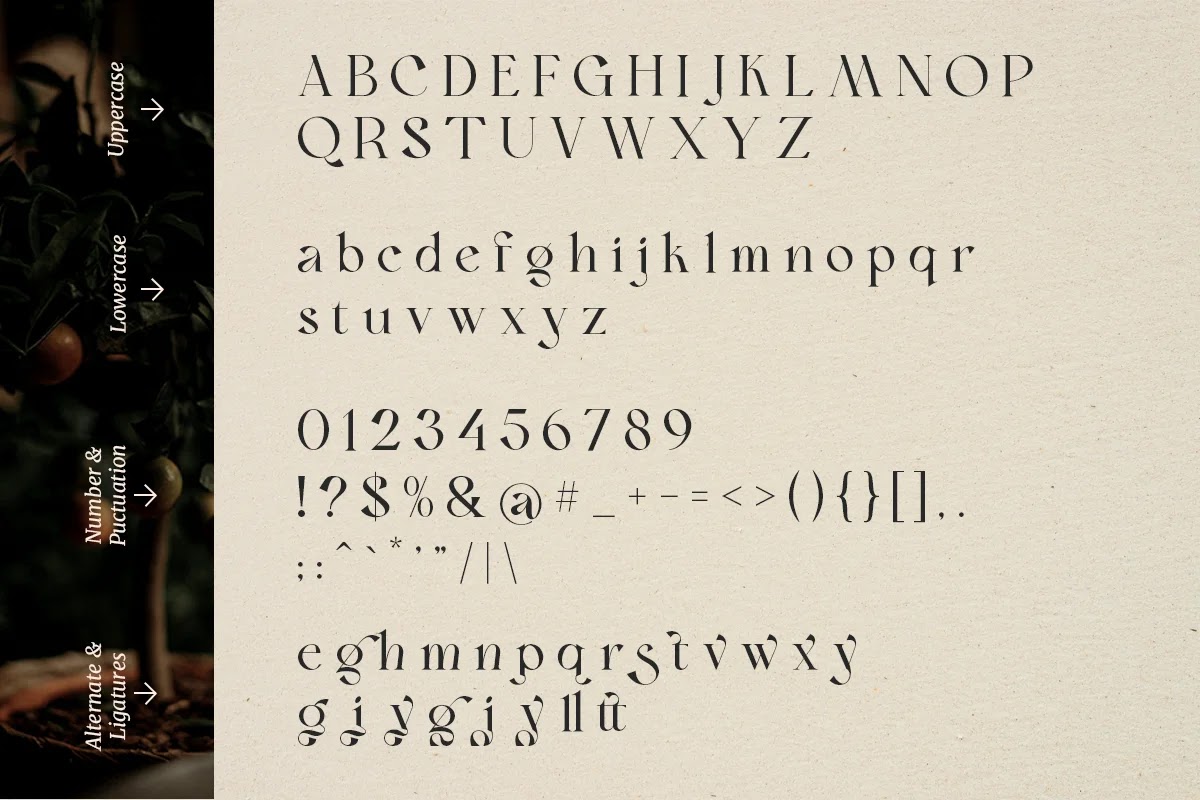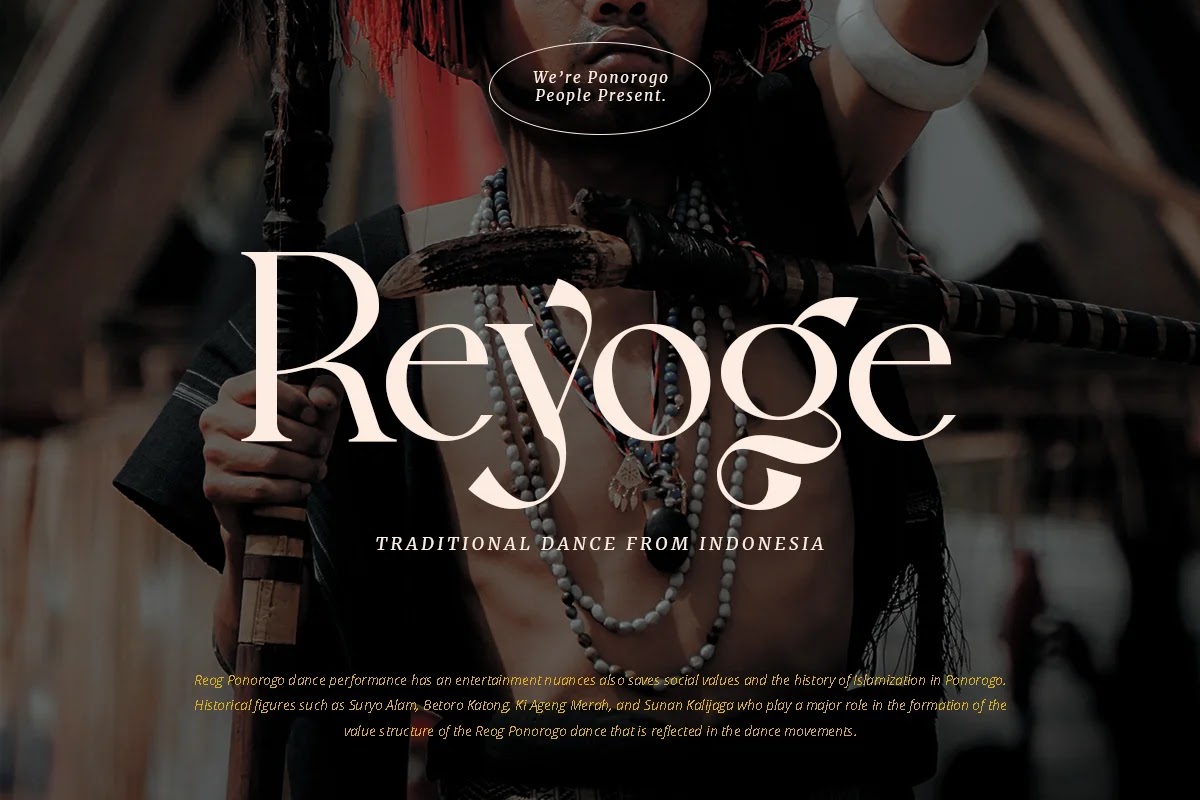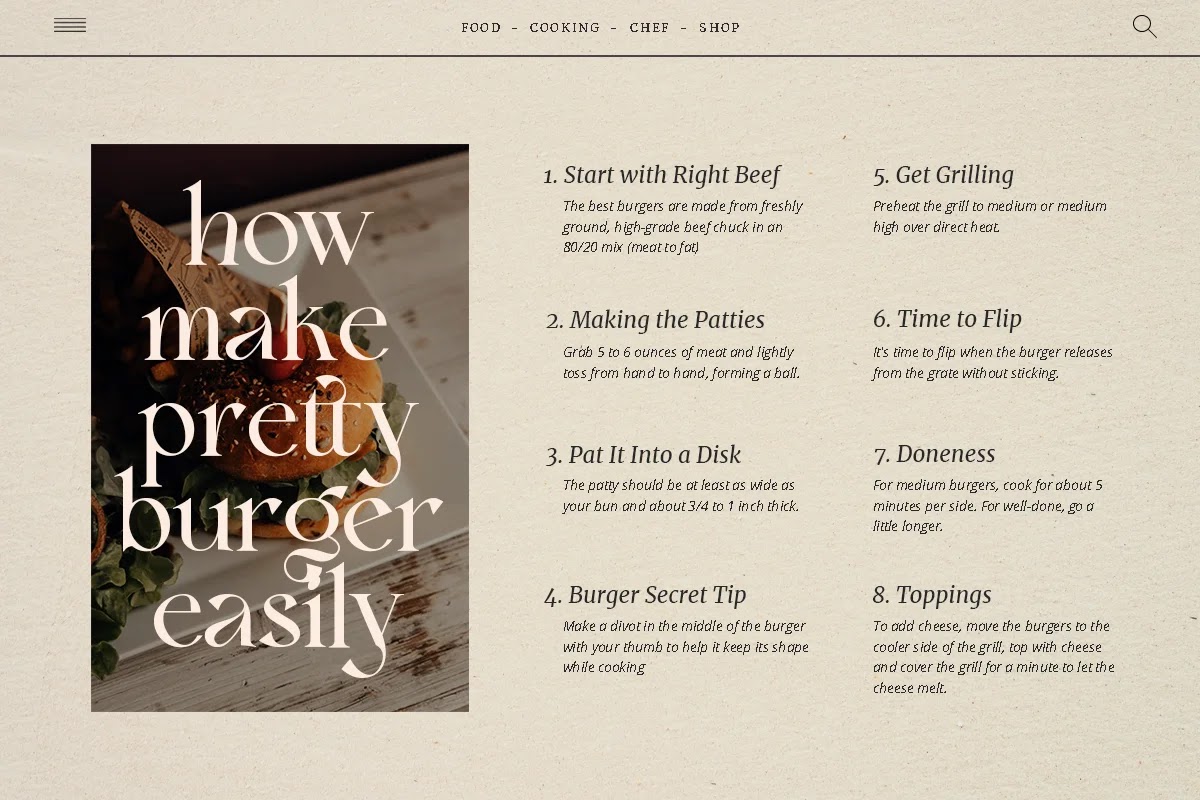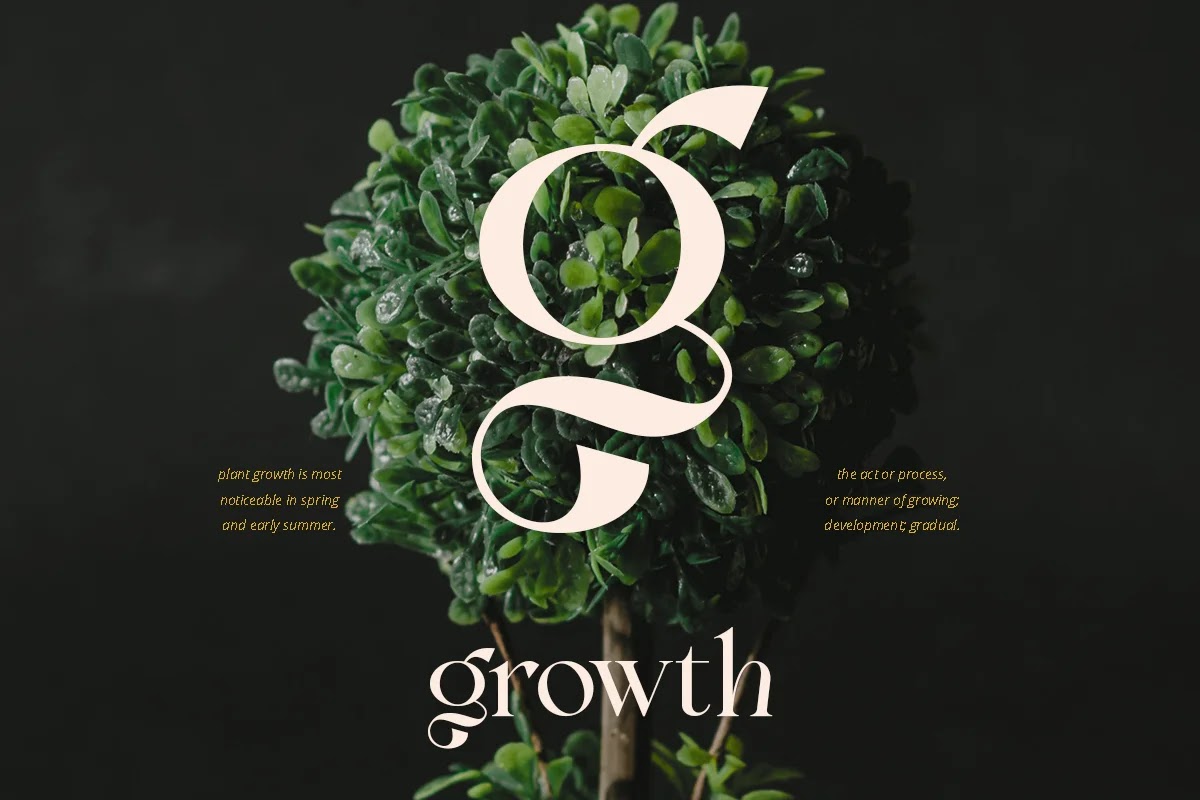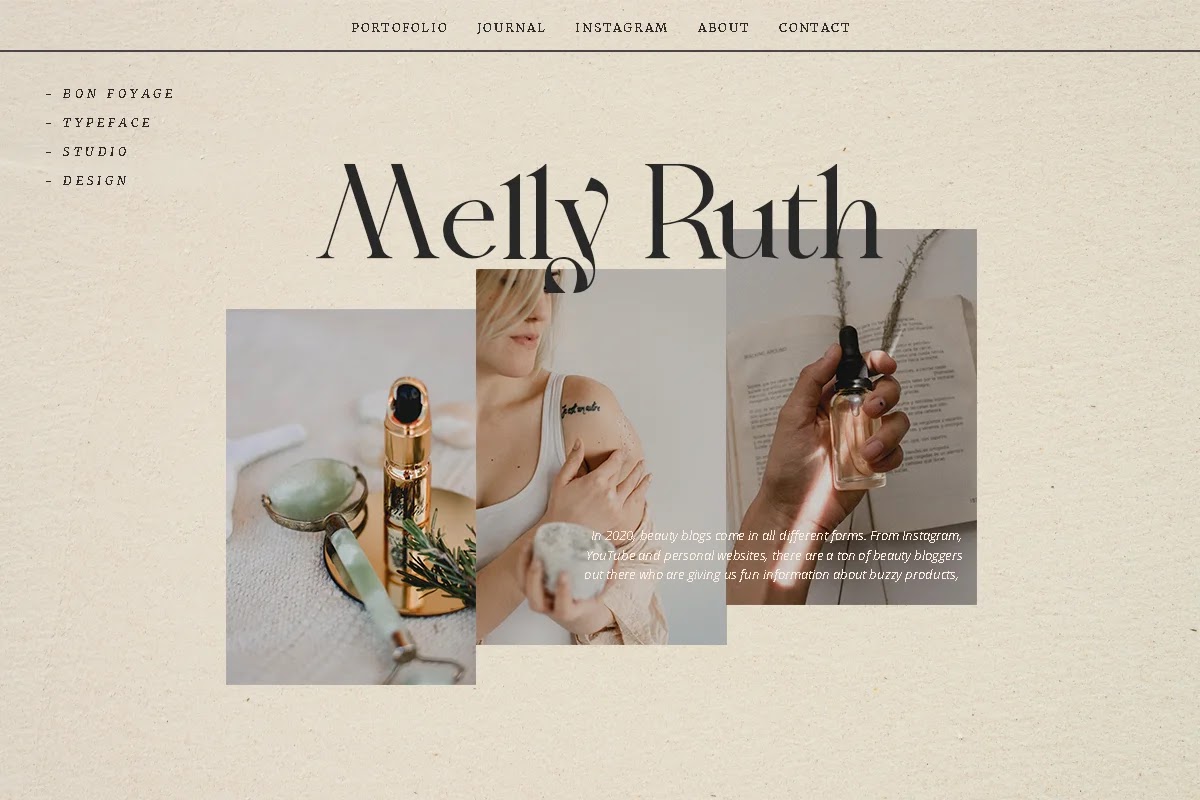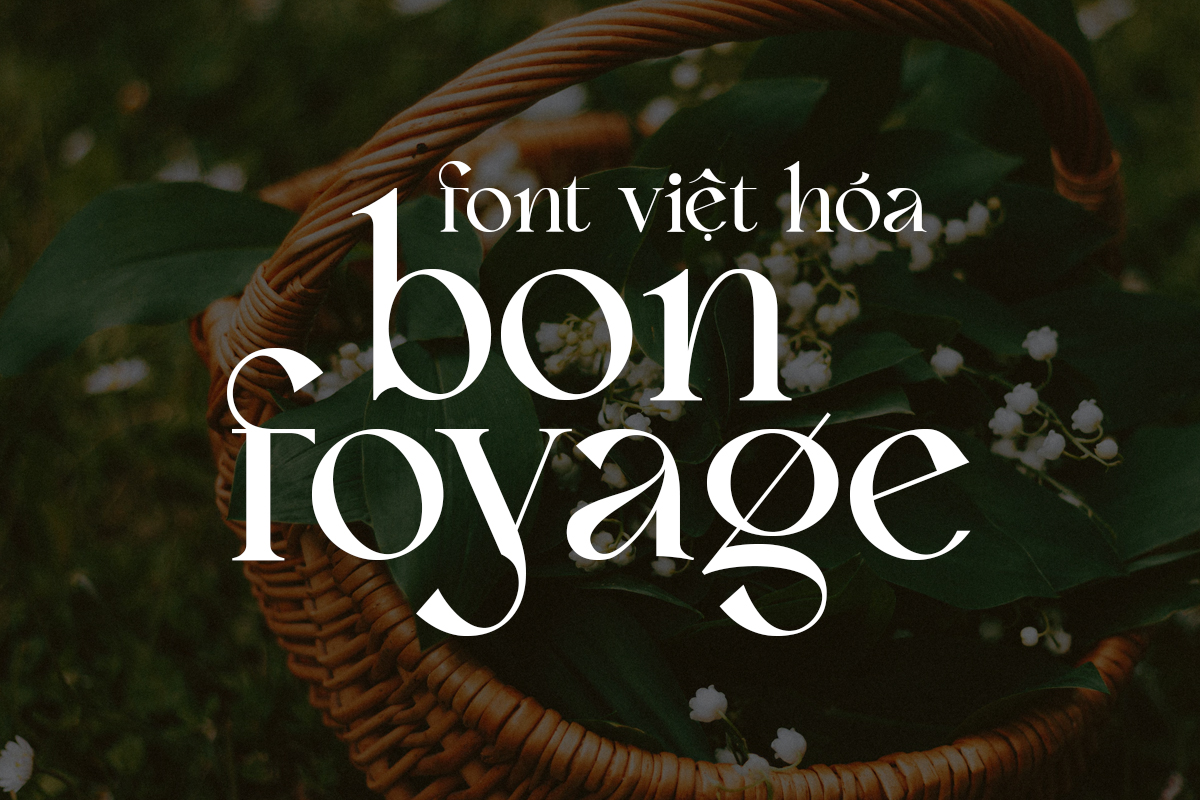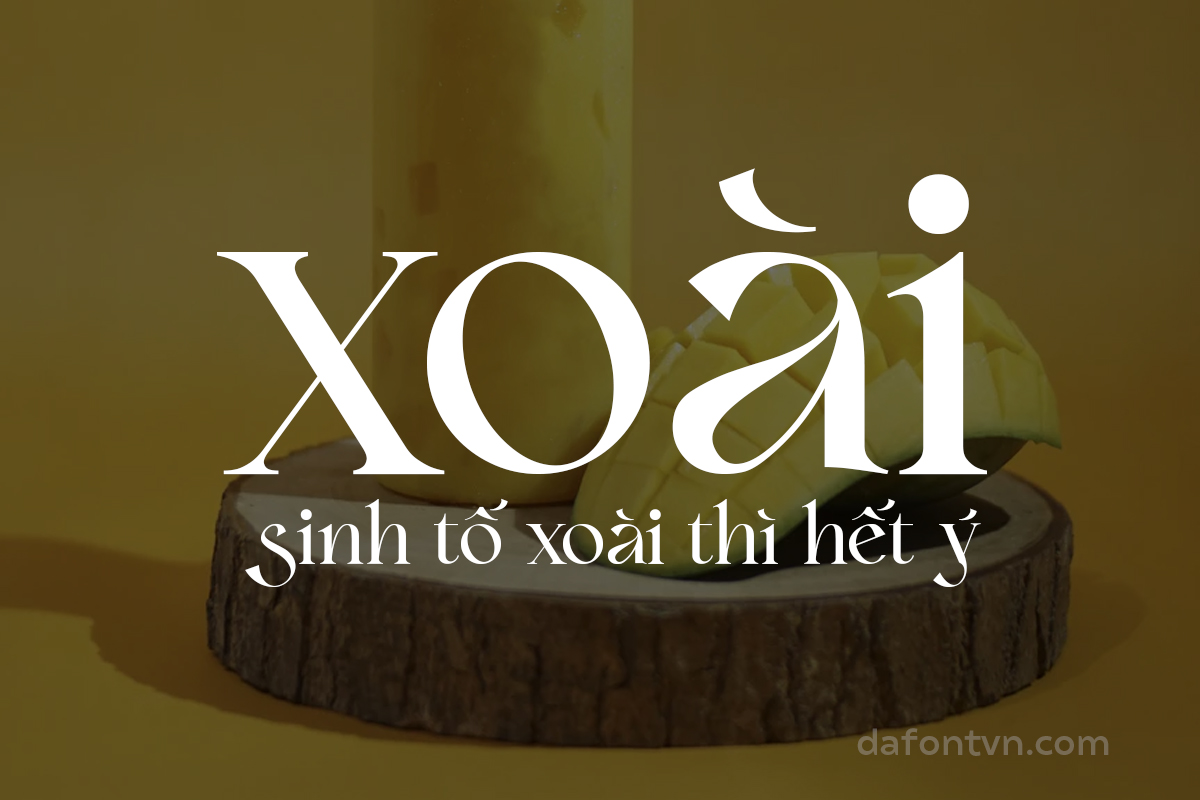
Font Bon Foyage Việt Hóa là một kiểu chữ serif cổ điển hiện đại với các mẫu chữ độc đáo, các nét chữ thay thế đẹp mắt và hỗ trợ đa ngôn ngữ hoàn chỉnh. Mỗi chữ cái đều có một nét độc đáo tinh tế đối với nó, từ các dạng chữ cái thay thế của “g, j, y”, những nét chữ này thật đáng thú vị!
Font Bon Foyage – Vintage Modern Serif hoàn hảo cho các dự án biên tập, thiết kế logo, xây dựng thương hiệu quần áo, bao bì sản phẩm, tiêu đề tạp chí hoặc đơn giản là lớp phủ văn bản phong cách cho bất kỳ thiết kế nào.
font Bon Foyage Việt Hóa
Font việt hóa Bon Foyage
Bon Foyage - Vintage Modern Serif